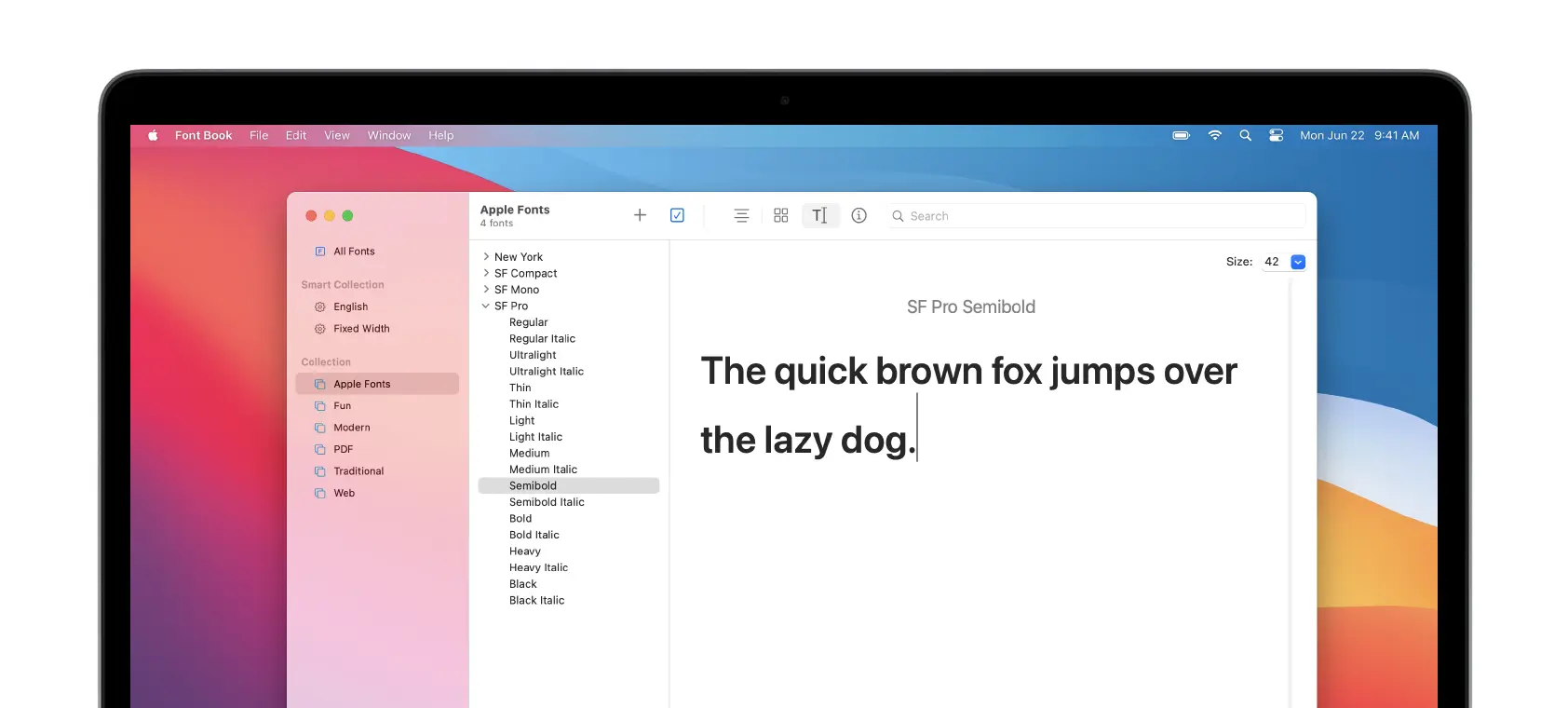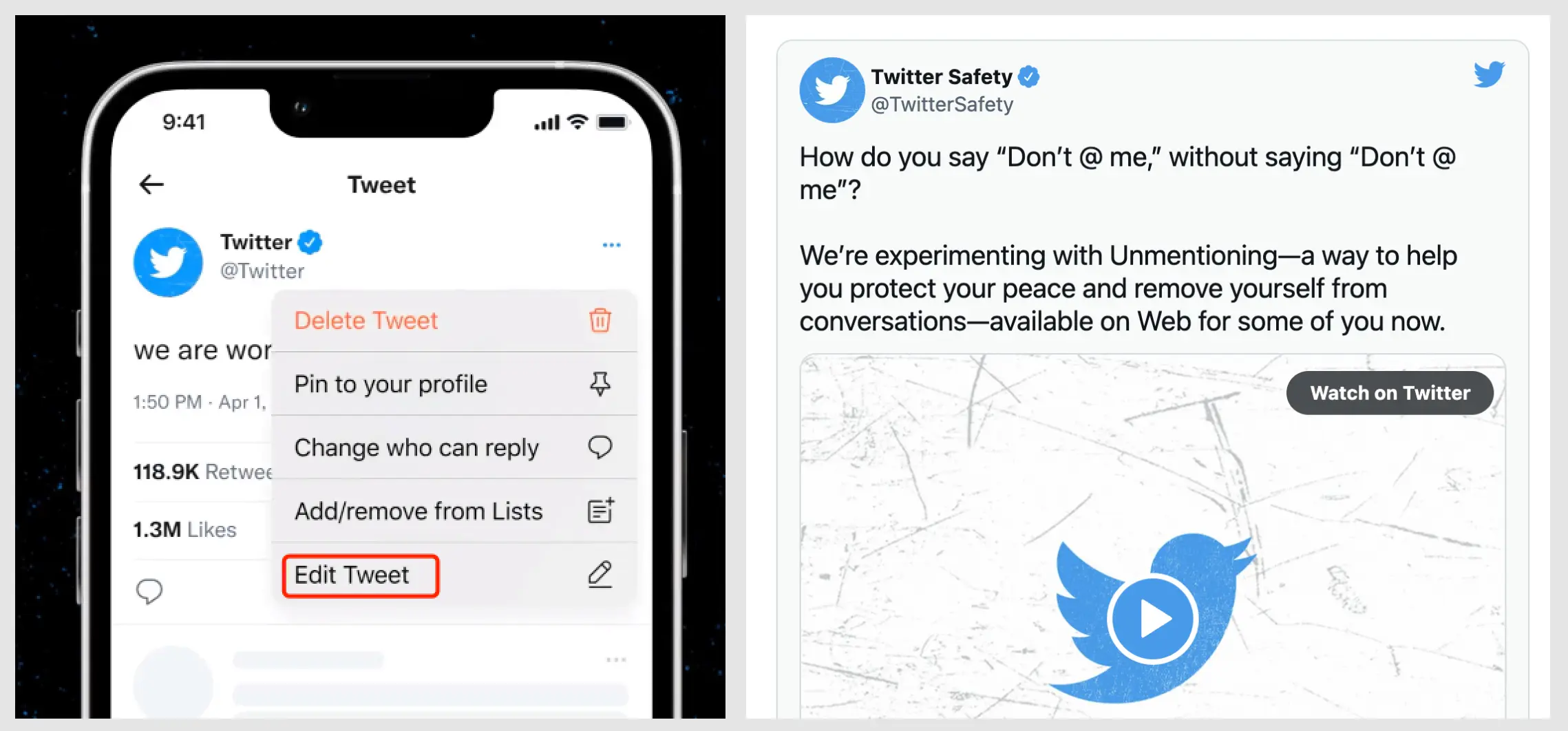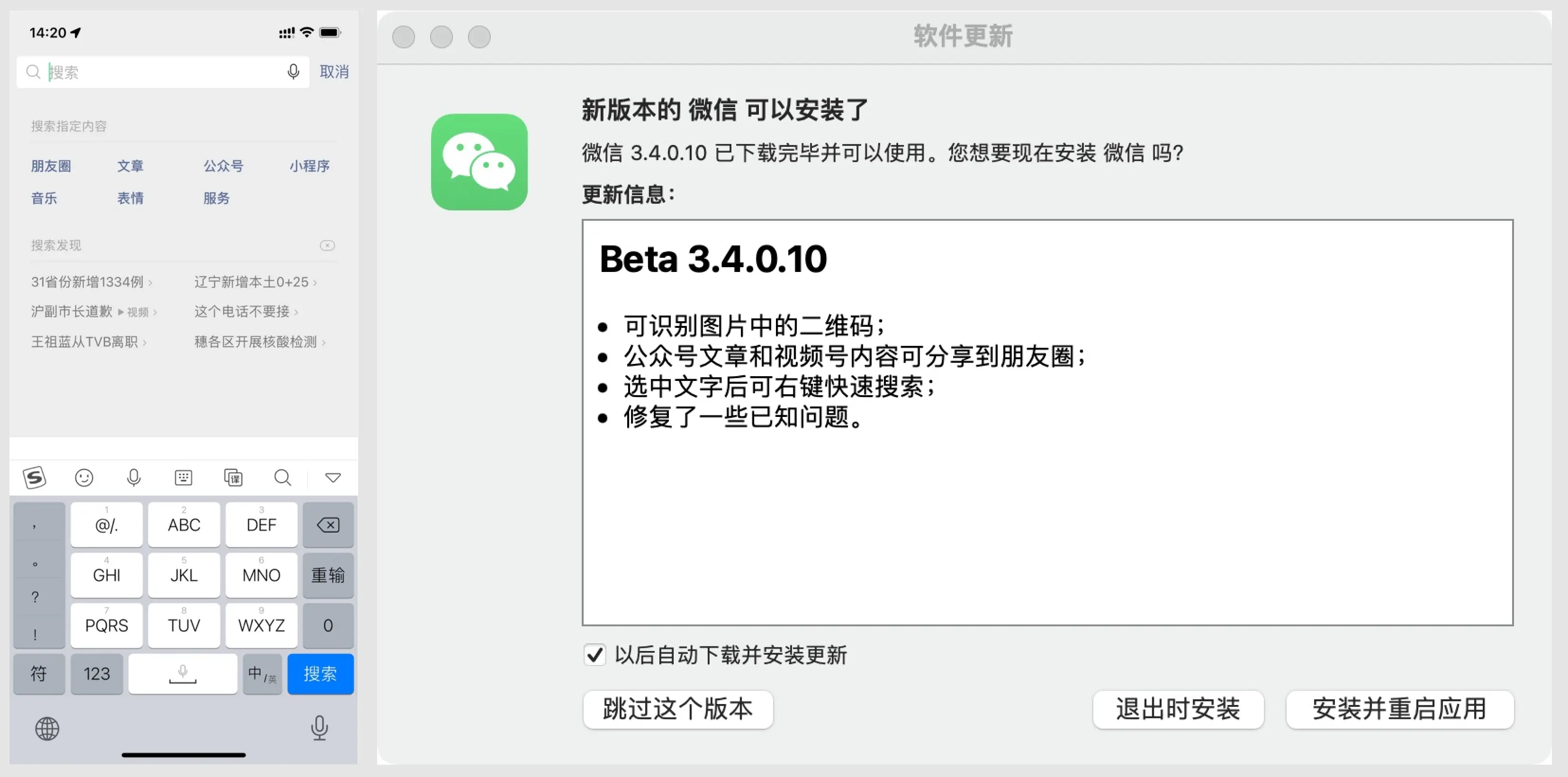
聊一聊系统字体的版权问题
系统字体
不管设计师在UI设计稿使用了什么字体,如果不做嵌入处理,最终呈现在软件上的字体都是搭载该软件的操作系统提供的默认字体,而字体嵌入除了考虑版权问题以外,还会增加产品包体积大小,而系统字体是用户手机或者电脑里预装好的,即用即取。
好的操作系统对于自己的默认系统字体是相当考究的,拿Apple来举例子:
San Francisco、苹方:
Apple生态操作系统的默认系统字体是 San Francisco —— SF家族,这个大家族为了满足不同的需求,拥有许多成员。比如SF Compat使用在watchOS 6,专为小屏幕设计。SF Pro则是 macOS、 iOS、 iPadOS 和 tvOS 的操作界面字体。SF Serif是家族的衬线体,也称为New York。SF Pro AR 是阿拉伯字体、SF Pro JP 是日文字体、SF Pro KR 是韩文字体、SF Pro TH 是泰语字体。
系统默认中文字体属于苹方家族,分别是苹方-简(PingFang-SC)、苹方-港(PingFang-HK)、苹方-繁(PingFang-TC),随着iOS9发布,苹方正式取代了之前的华文黑体。以及你可以理解SF Pro SC和PingFang SC是一种字体。
所以一些新UI设计师在设计简体中文APP时,使用PingFang-HK和PingFang-TC作为设计稿字体是不合规范的。
除此之外,苹果还为提供了许多额外的字体供开发者们使用。例如,你打开字体册。选择电脑这一栏:
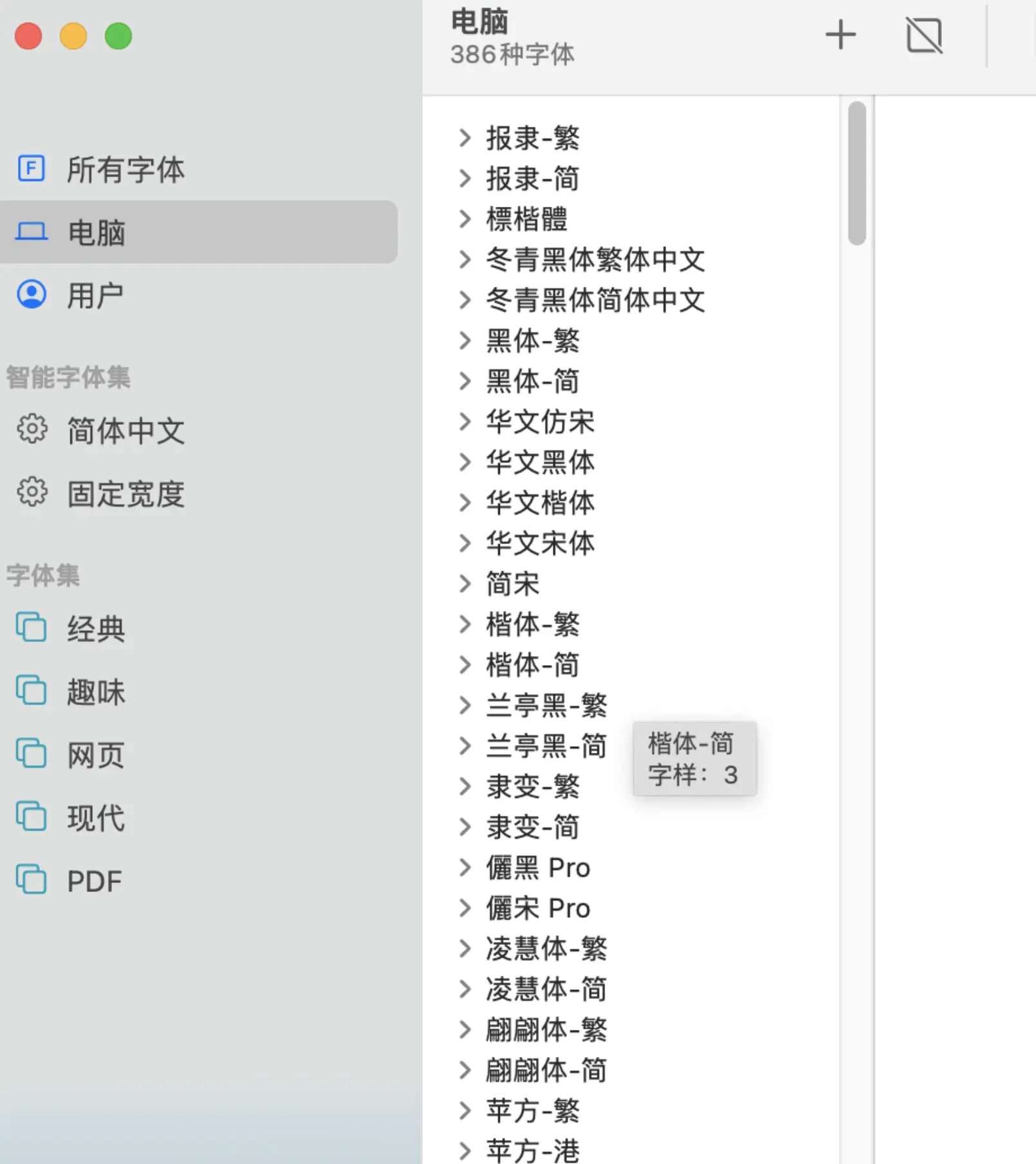
根据苹果的描述,预装字体都是可以免费使用到用户界面里的,只要是基于苹果的操作系统。
这些是非常大的福利了,举个例子,苹果系统自带的Avenir的商业授权是非常昂贵的,然而因为苹果与字体公司签署了授权协议,所有苹果用户都能免费使用Avenir到他们的基于苹果操作系统的产品界面,不管是商业还是个人用途。
那么如果我的产品在Android系统是否也能使用Avenir呢?答案是不可以,因为Android的系统并不提供该英文字体,若想使用的话需要将字体嵌入到产品中,而这一点是不包括在苹果的字体使用协议里的。
跨平台嵌入系统字体是侵权的。
而这一套规则目前来看是属于每个操作系统的基本福利。比如你是Windows用户,使用系统字体到自己基于Windows的产品界面里。或者Android产品使用Android的系统自带字体。
但是打印品?得分情况
所有设计师也许前几年都看见过这样一个标题《什么?微软雅黑居然不能用作商业打印》,作为Windows的内嵌系统字体微软雅黑,只能免费用于屏幕显示或用于个人为目的的打印,商业打印是需要授权的。但Windows有些内嵌中文字体又是允许商业打印的,例如华康的新细明体、标楷体。
而良心的苹果爸爸更加照顾到大家,OS X签了许多中文字型的授权,像是苹方(华康)、娃娃体(华康)、魏碑体(文鼎)、苹果俪细宋、苹果俪中黑、宋体-繁、楷体-繁,还有其他很多字型,无论是哪个厂商提供给Apple的,只要是Mac用户,都可以将这些字型用于商业使用(包括打印),包括上面提到的昂贵英文字体Avenir。
但是出于保险,使用系统字体打印商业用品时,建议大家最好还是先查询一下相关协议。